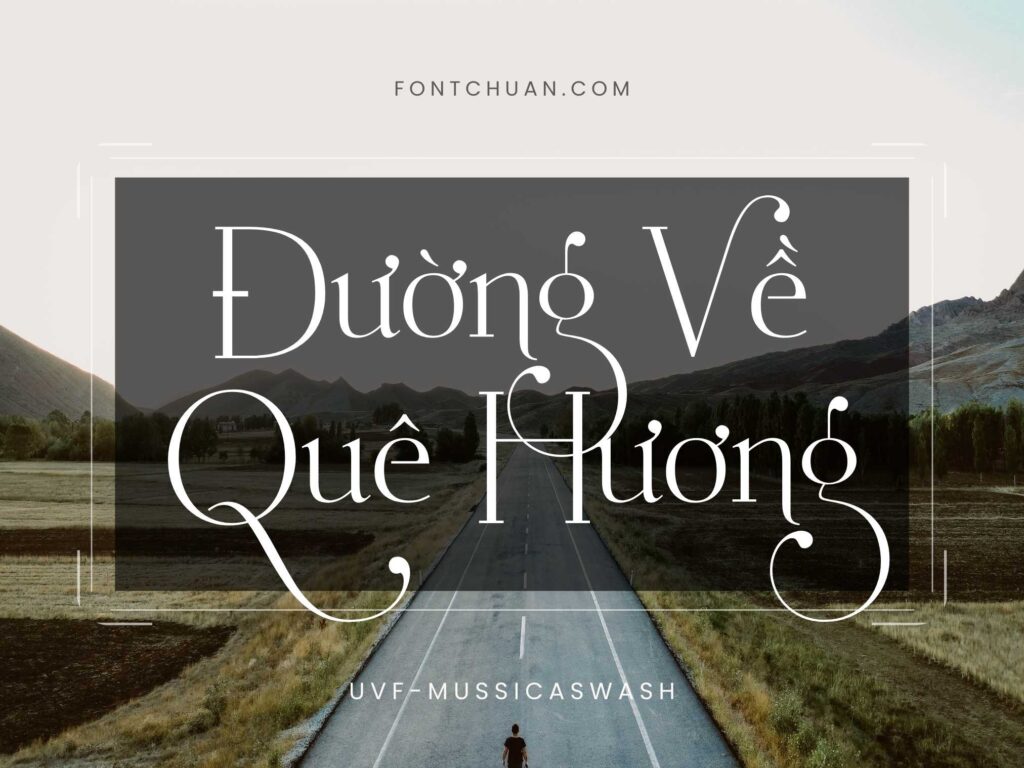
Font UVF Mussica Swash Việt Hóa
Mussica Swash là một font chữ trang trí với các đường nét uyển chuyển và tinh tế, được thiết kế bởi Manuel Eduardo Corradine vào năm 2009. Font này nổi bật với các nét chữ mảnh mai kết hợp với những đường cong mềm mại, tạo nên vẻ đẹp thanh lịch và độc đáo. Mussica Swash đã được Việt hóa, giúp người dùng tại Việt Nam dễ dàng sử dụng trong các dự án thiết kế của mình.
Với thiết kế độc đáo, Mussica Swash phù hợp cho các ứng dụng như thiệp mời, tiêu đề, logo, và các ấn phẩm nghệ thuật. Trong lĩnh vực sự kiện, font này có thể được sử dụng trong các dịp như lễ hội, lễ cưới, và các sự kiện văn hóa. Ngoài ra, Mussica Swash cũng thích hợp cho các ngành nghề như quảng cáo, thiết kế thiệp cưới, và nghệ thuật trang trí.